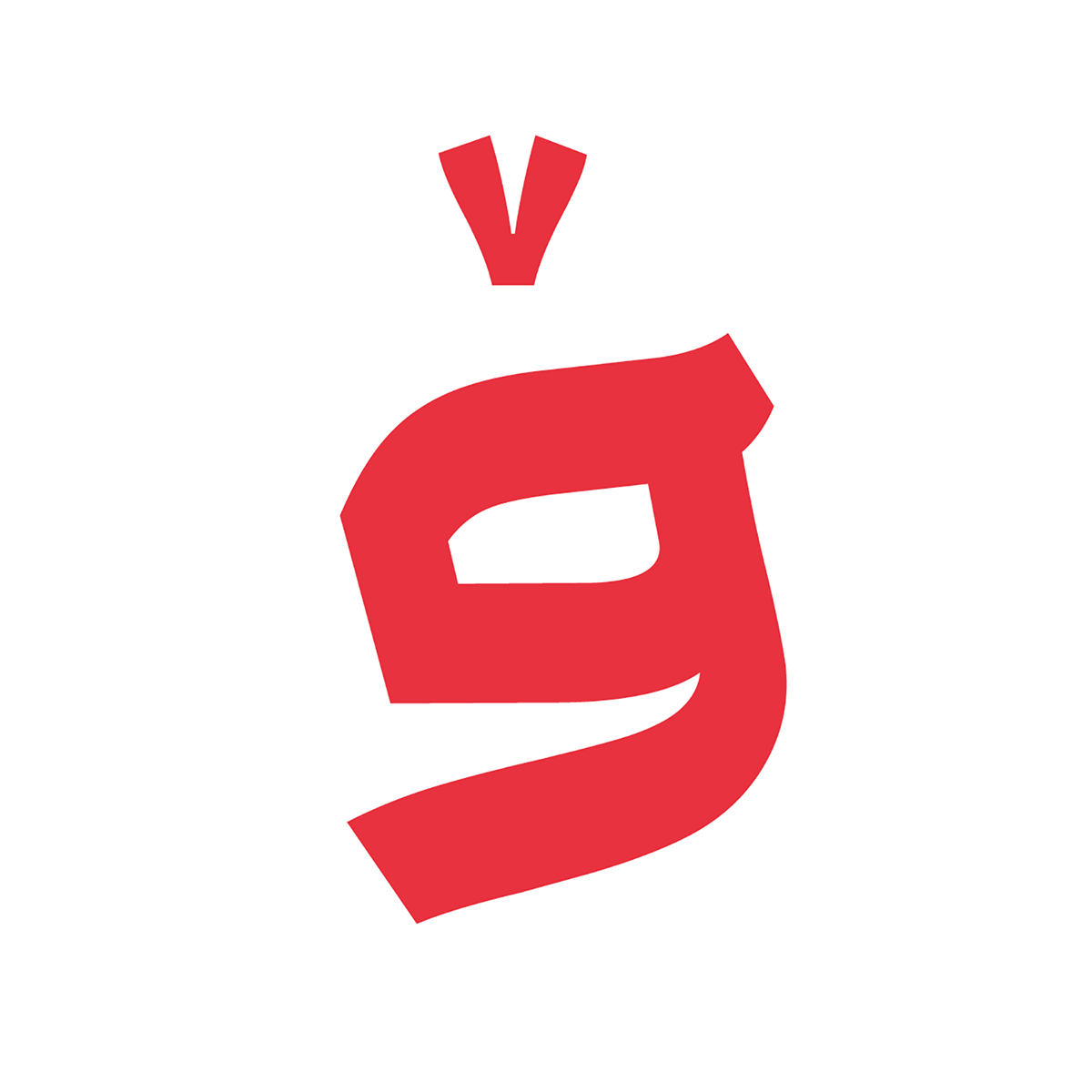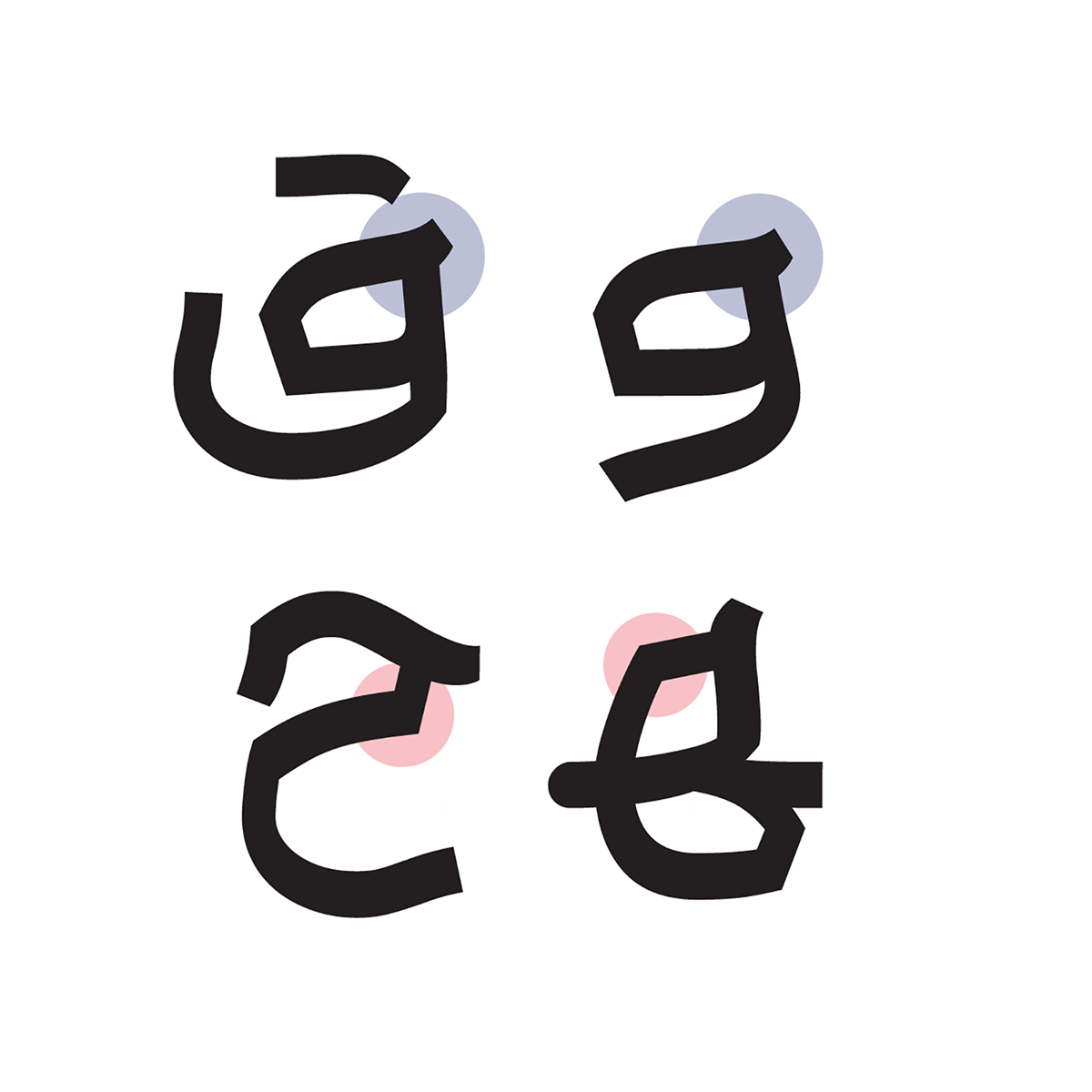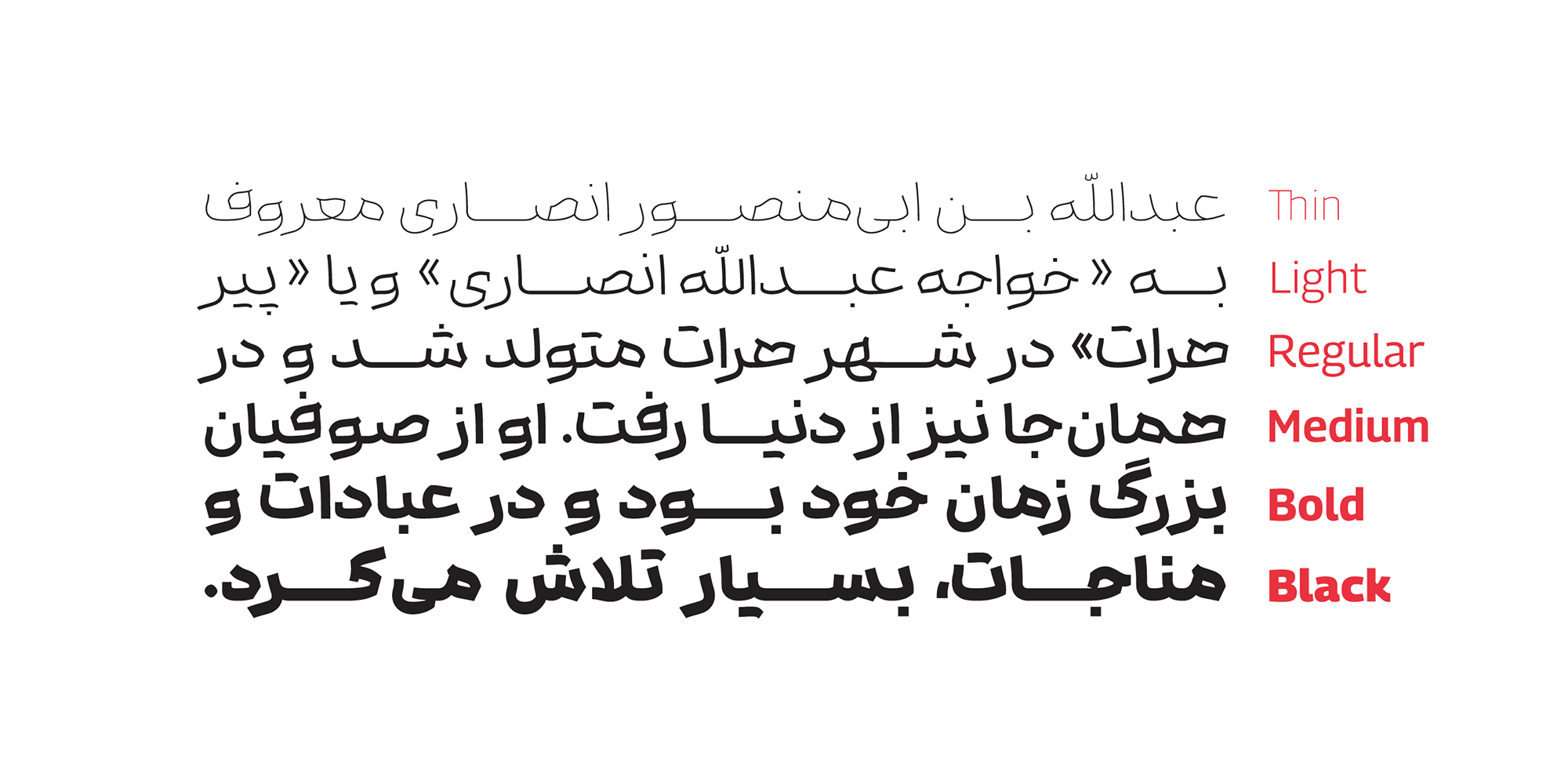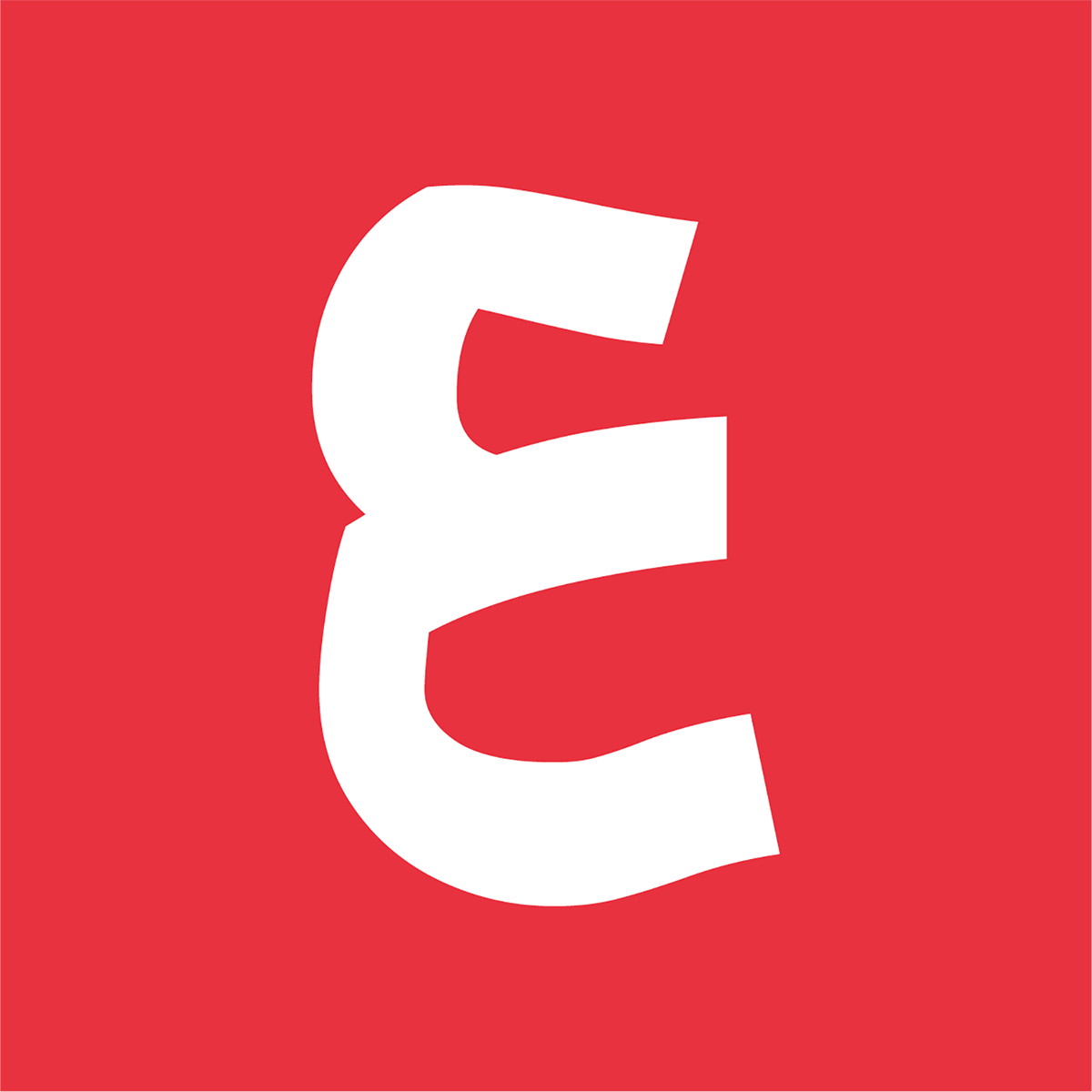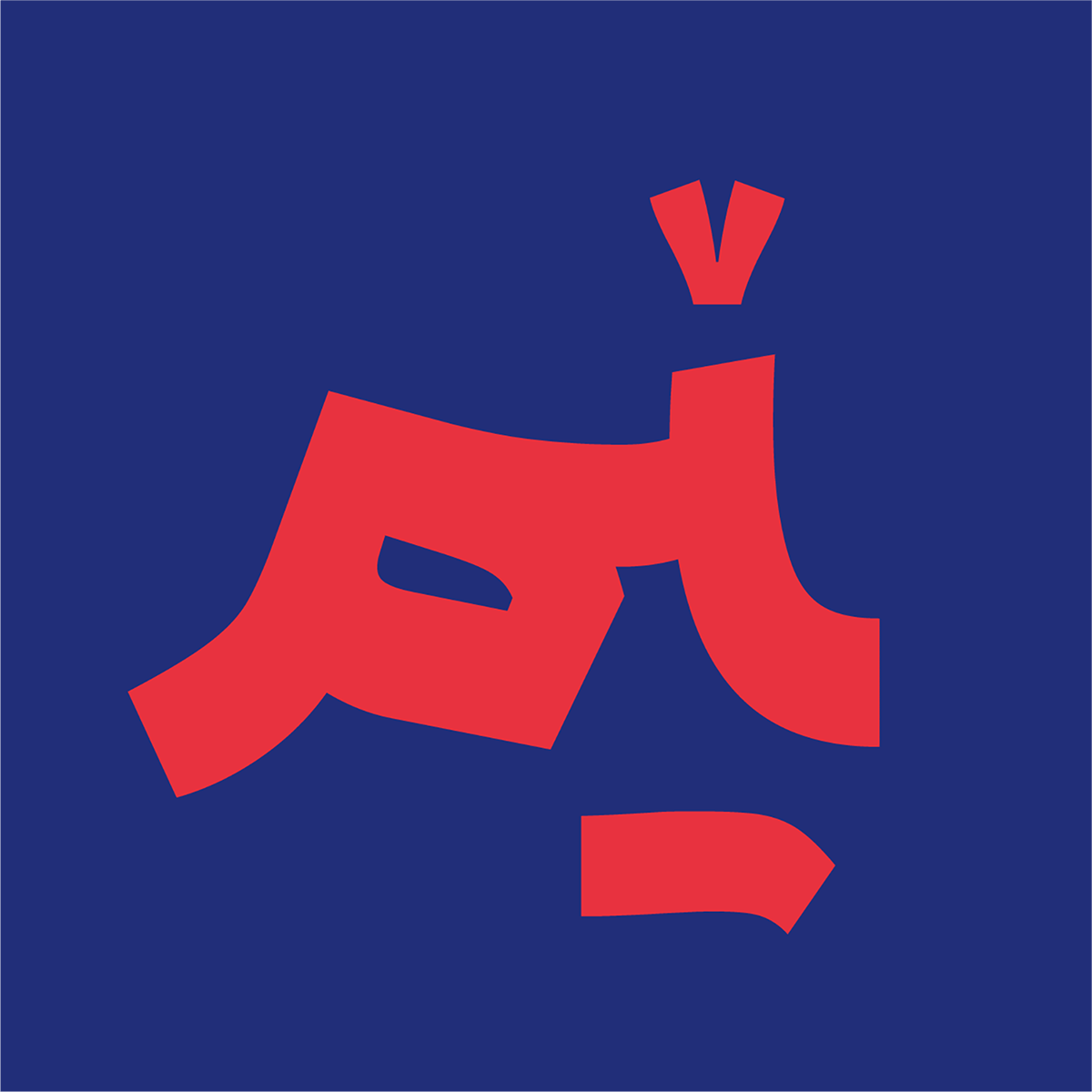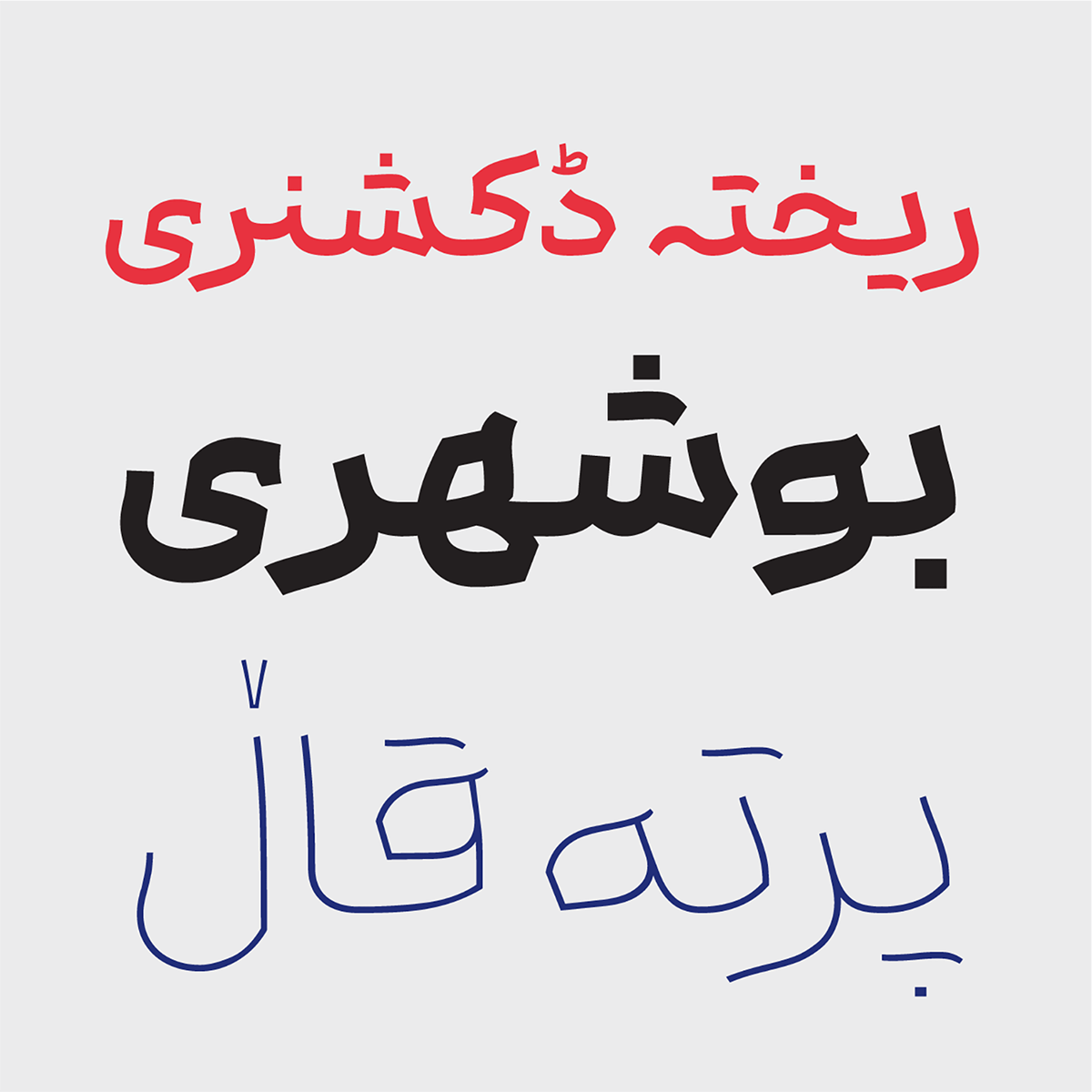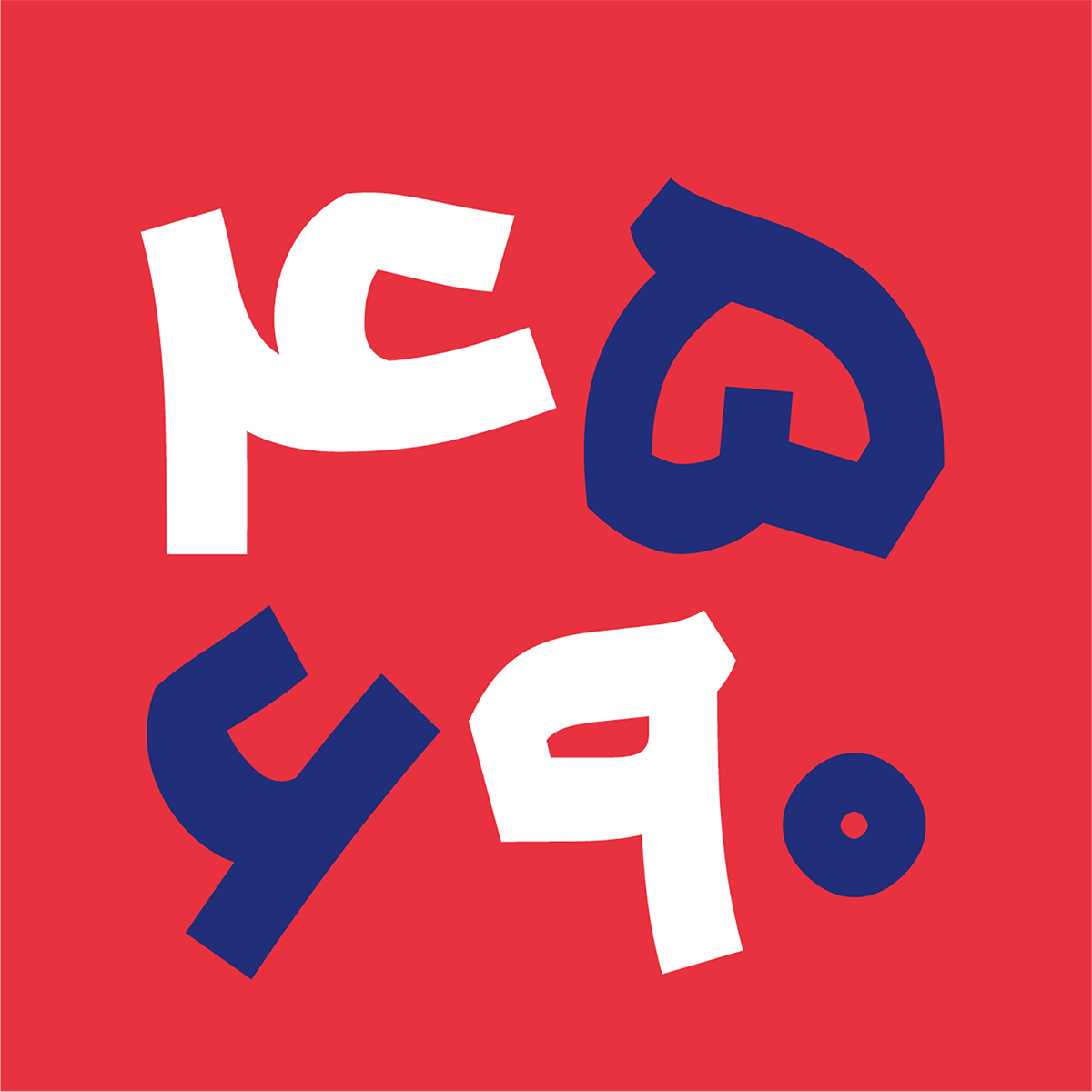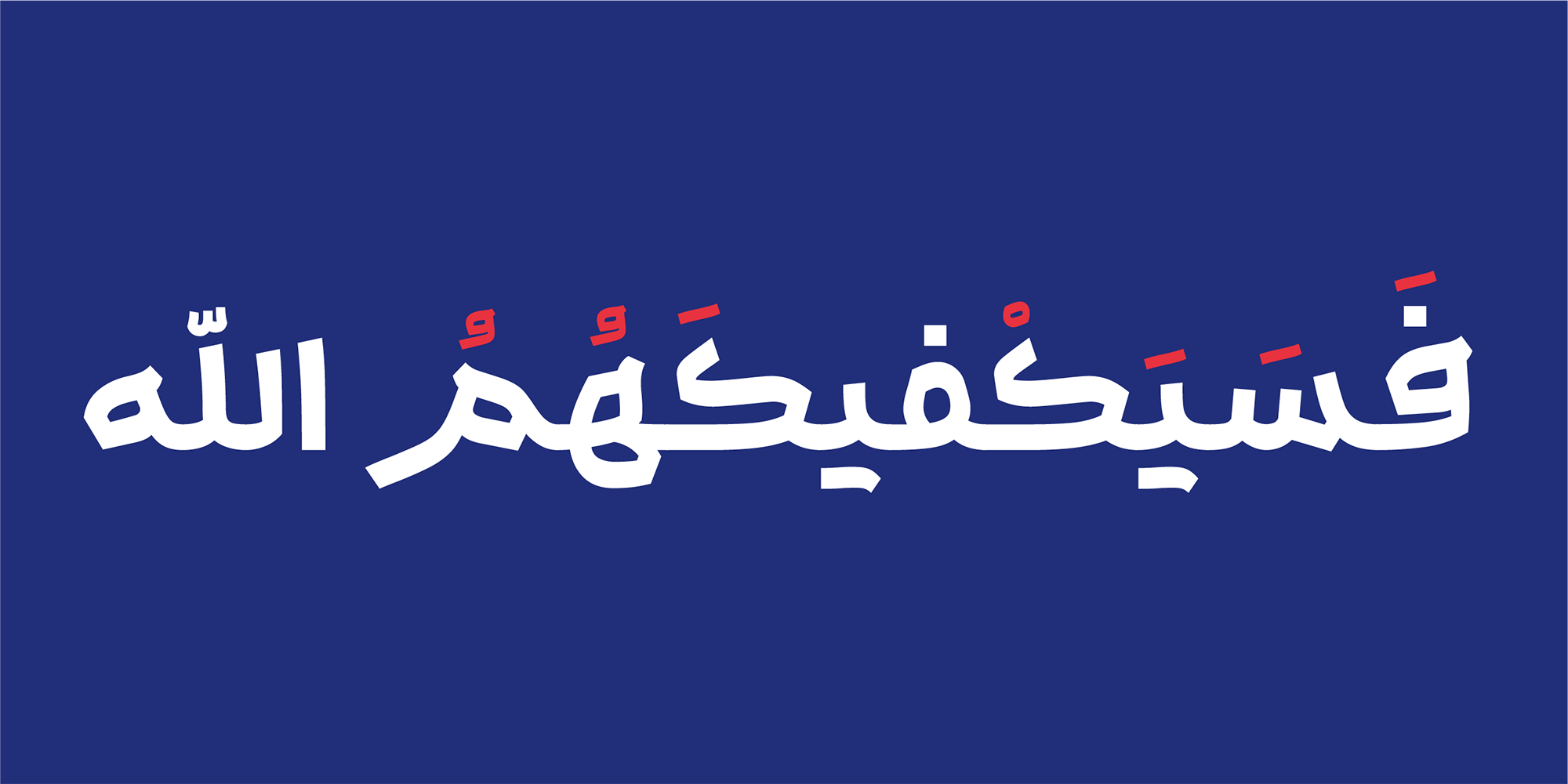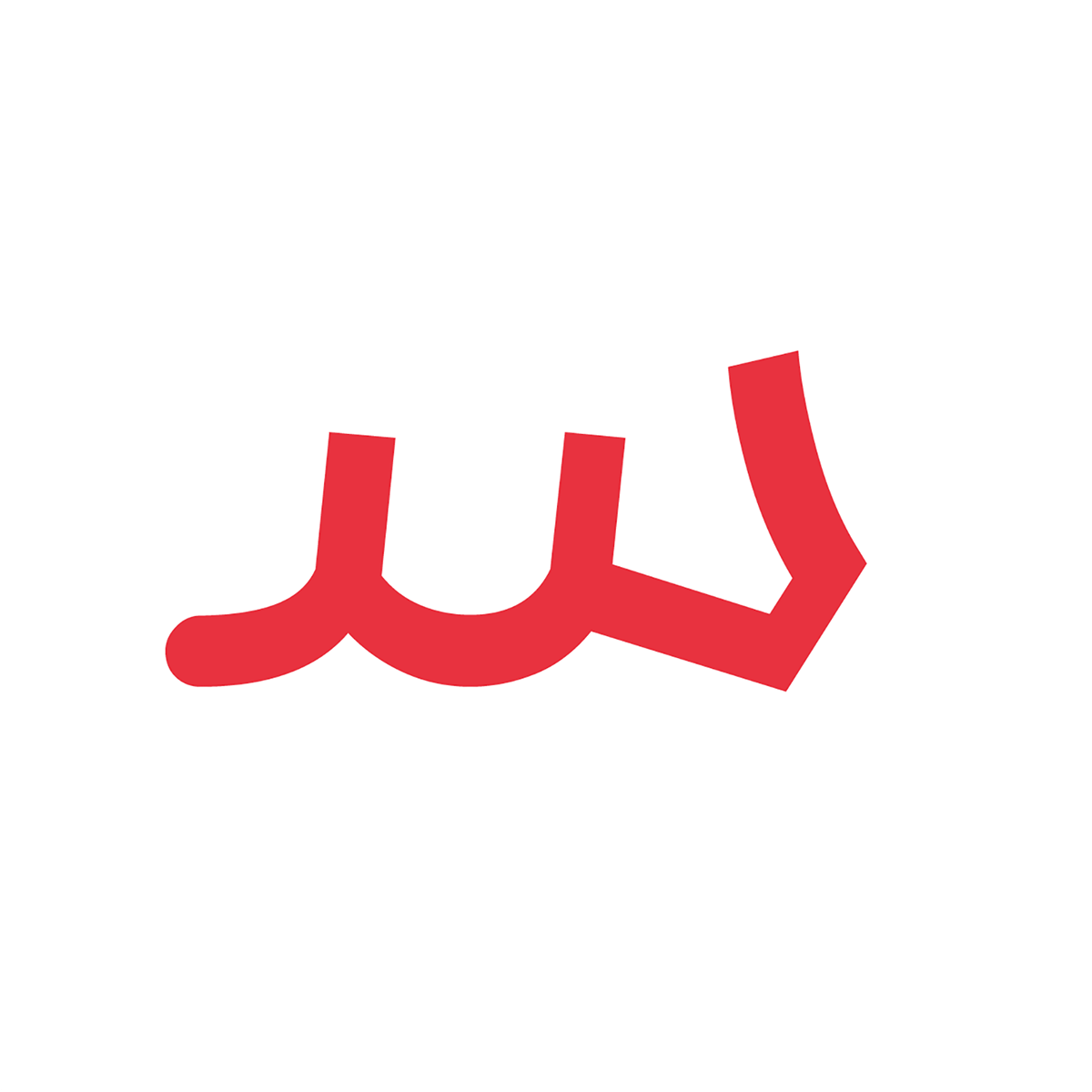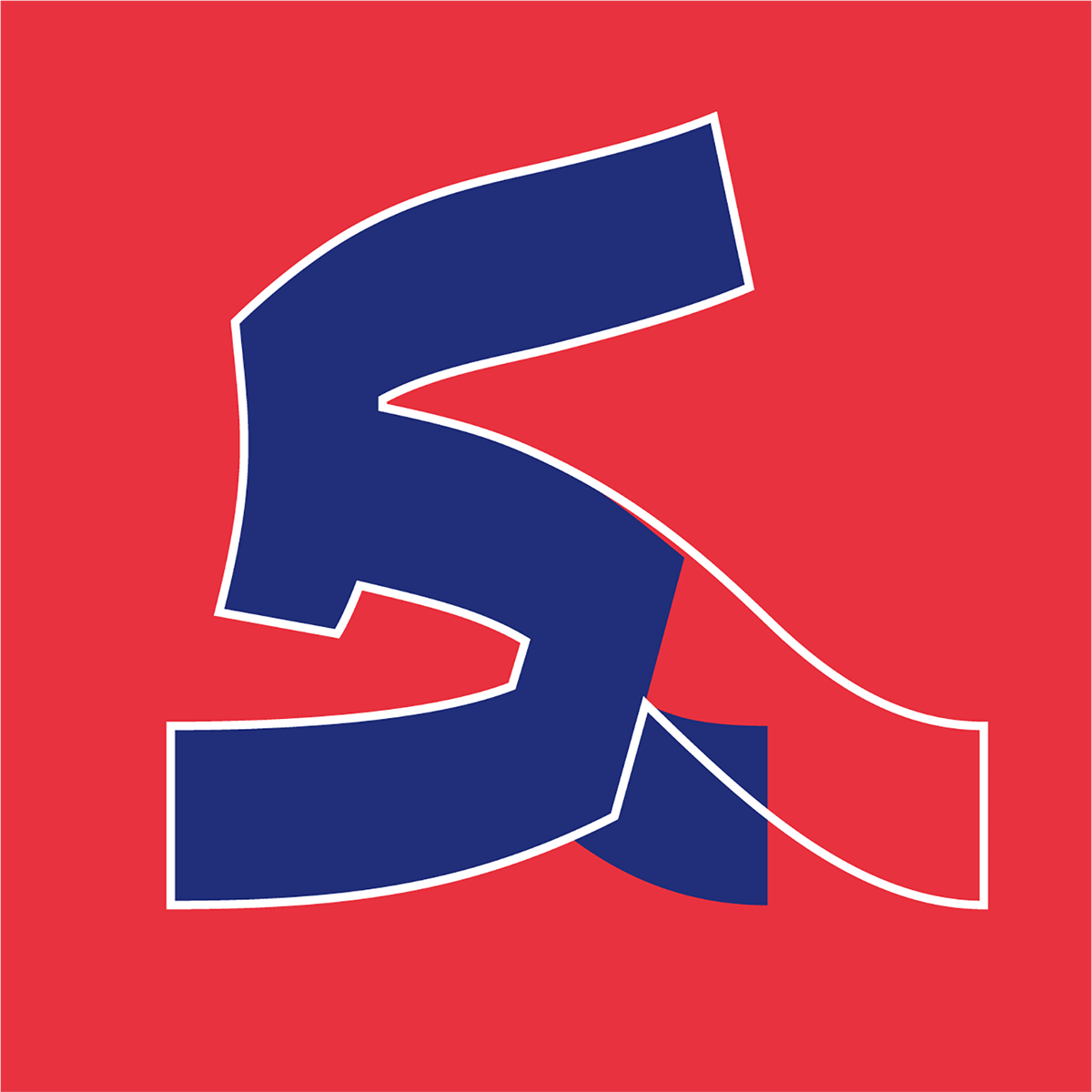
تنوع وزنها در فونت باوان
باوان یک خانواده فونت با ۶ وزن است که از نازك تا ضخیم را در بر می گیرد. این فونت از تایپ انگلیسی Georama برای بخش لاتین بهره میگیرد.
فونت باوان دارا استایل ها و لیگیچرهای متفاوت و جذاب است. برای مثال از دو نوع اتصال ک بهره مند است.